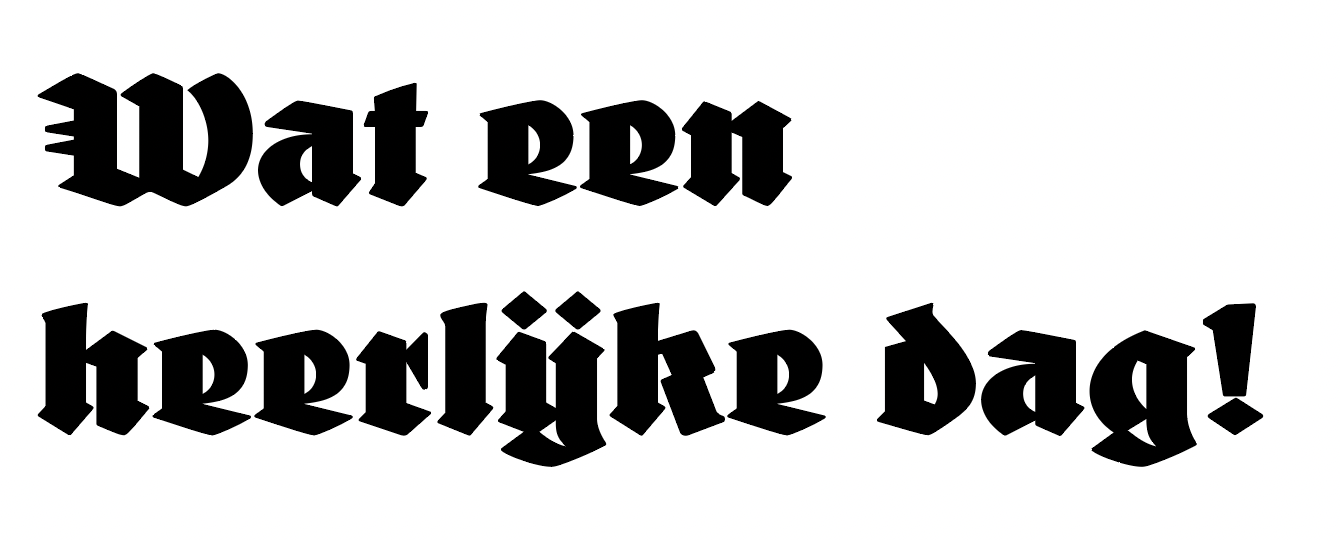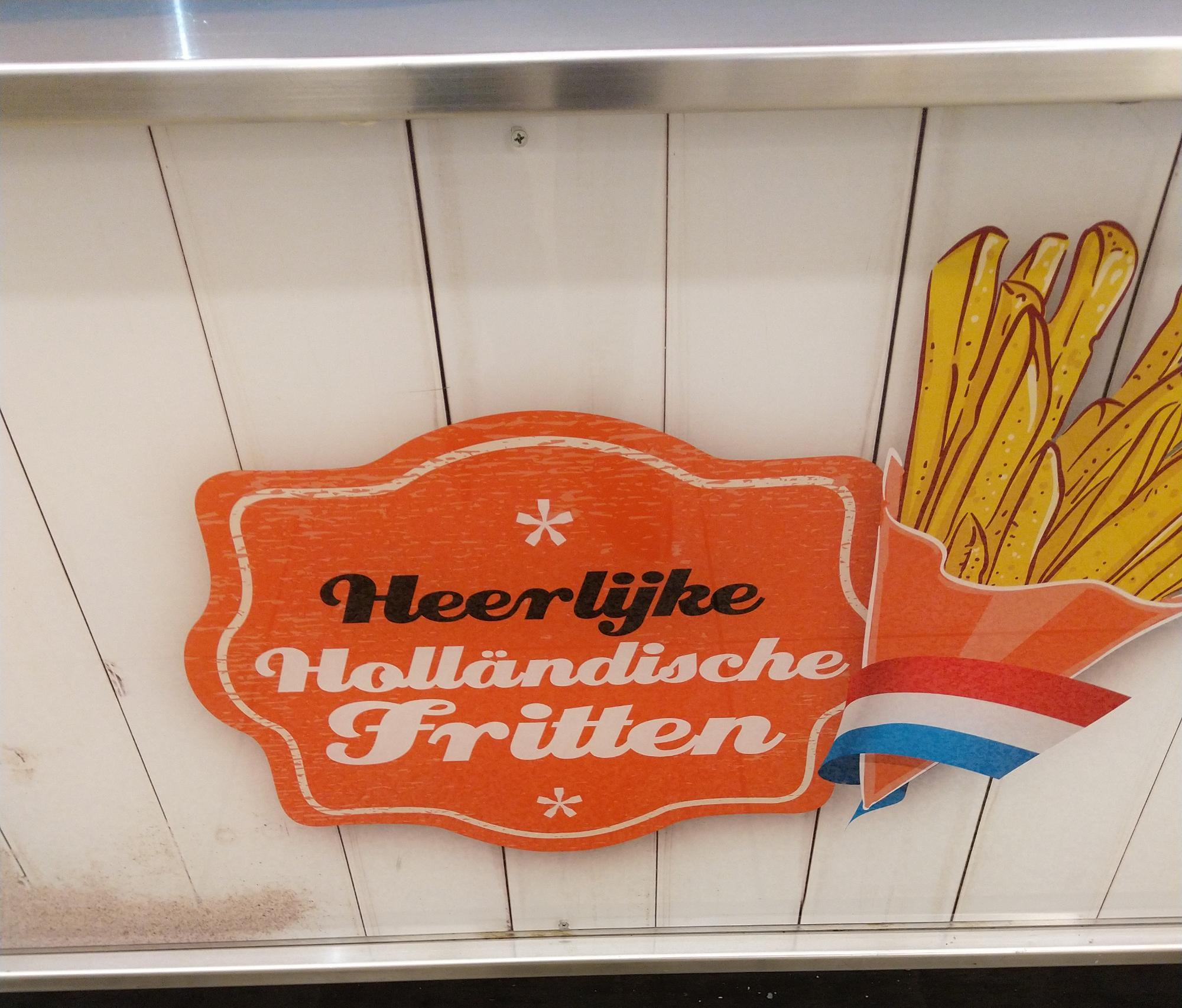
Ist das ein Y oder ist es eine Ligatur aus i und j?
Das ist nicht mehr genau feststellbar. Handschriftlich ist sowohl das y mit Trema als auch als Digraph ij im Gebrauch. Daher kommt es darauf an, ob das in der jeweiligen Schrift als Ligatur (Versalie: U+0132 Gemeine: U+0133, auch wenn die nicht empfohlen werden für Archivierung) hinterlegt ist oder nicht. Beim Gebrauch bitte beachten, dass es dann IJsselmeer und nicht Ijsselmeer geschrieben wird.
Y
Abwegig ist das nicht, denn in einigen eingewanderten holländischen Familiennamen wurde das ij zu y (z. B. »Verweyst« wie in der Familie meines Onkels).
Historisch ist es ähnlich verwirrend wie beim ß. Man darf nicht vorschnell von »es sieht aus wie« zu »es ist« springen. In der aktuellen Anwendung ist das deutsche »-lich« eben ein »lijk« im Niederländischen. Wie am Großbuchstabenanfang von IJsselmeer zu sehen, ist es aber ij/IJ. Die Y-artigen Schreibungen sind heute eher eine grafische Spielart, insbesondere bei Handschrift und Druckschriften mit Schreibschriftcharakter. Im Wörterbuch würde heerlijk stehen, nicht heerlyk oder heerlÿk.
Ich baue es mittlerweile auch gern in meine gebrochenen Schriften ein. Sind ja auch in gewisser Weise Schreibschriften.
Letztlich sind ij, ij, y mit Trema und auch das y alleine (auch ü und allerlei andere Akzente auf den Buchstaben i, j, y und u hab ich gesehen (wobei die u-Varianten handschriftlich und selten sind) Allographe, die aber durchaus Heterophone bezeichnen können. Entwickelt hat es sich wahrscheinlich aus einem mittelniederländischen ii (Doppel-i), bei dem die Verdoppelung ein Longum kennzeichnete. Daher ist die Aussprache heute auch nicht gänzlich einheitlich. Es reicht vom Deutschen ei bis zum zum Russischen й und auch mal Ы.
Aufgrund der Abstammung aus dem handschriftlichen Corpus hat sich keine echt einheitliche Repräsentation gebildet, da es auf die Eigenheiten der Schreiber und der schriftlichen Umgebung ankommt, den entsprechenden Laut in einem bequemen Zug zu schreiben.
Nicht zuletzt deswegen, weil das y als Ypsilon nur in Fremdwörtern im heutigen Niederländisch vorkommt. Ob das ij tatsächlich zum niederländischen Alphabet gehört, ist auch nicht wirklich feststehend.
Wenn's das richtige is: g l mit Strich und Ogonek. Das findet in der Archisprache Verwendung (ob nach g weiß ich nicht). Die Sprache wird in sieben Dörfern im nordöstlichen Kaukasus gesprochen.
Auch jetzt, daß ich's weiß, werdet ihr diesen Glyph in meinen zukünftigen Schriften vergeblich suchen.